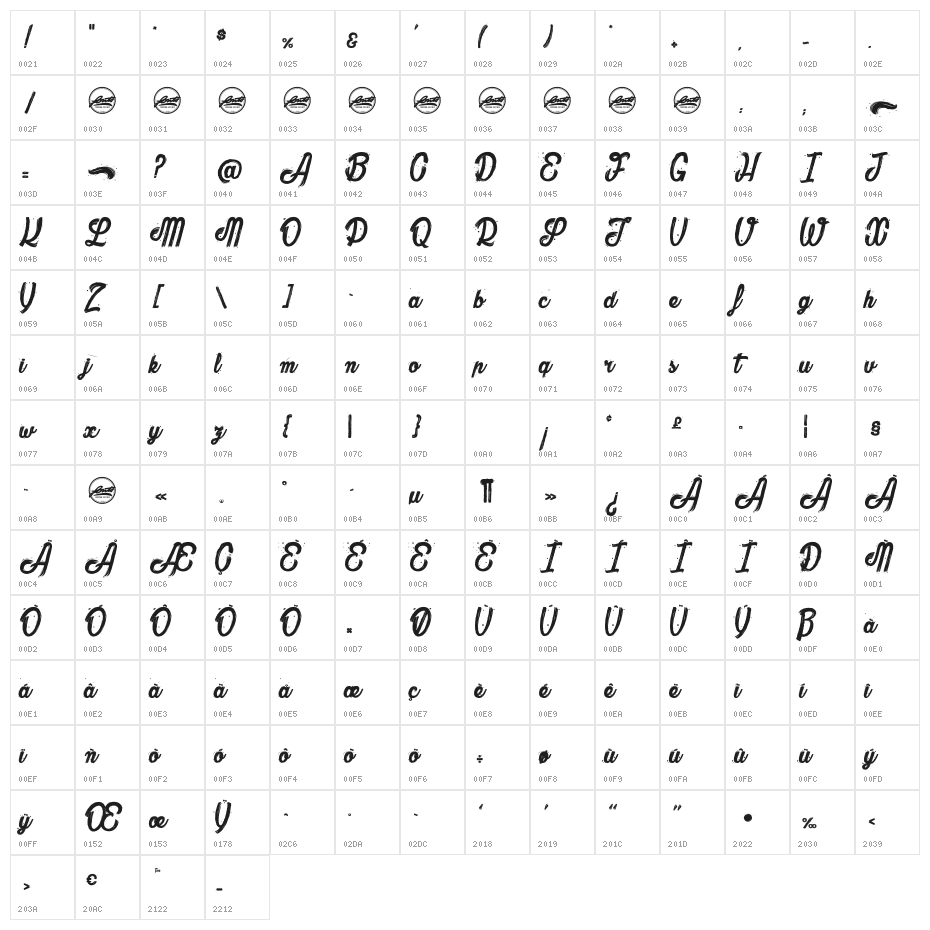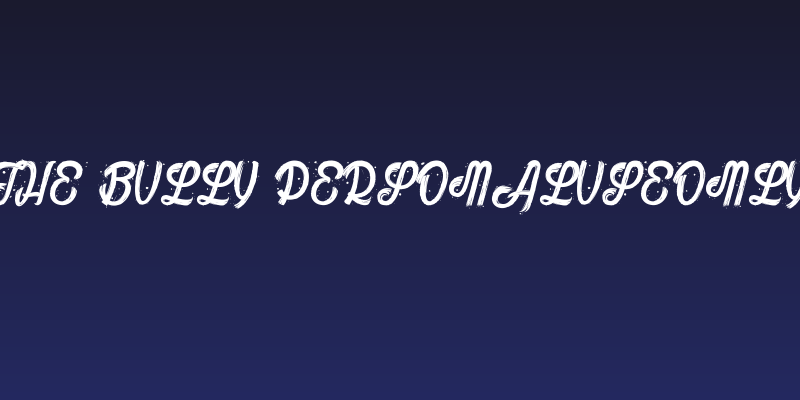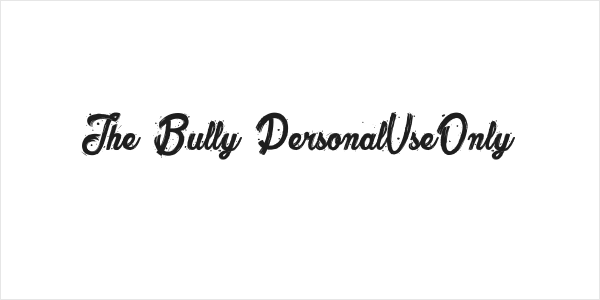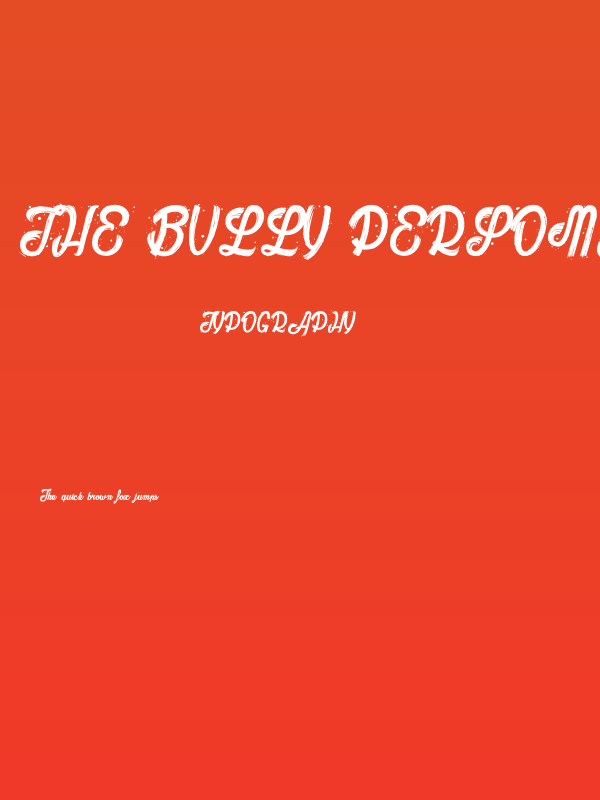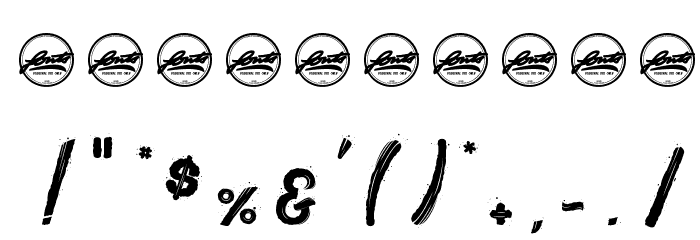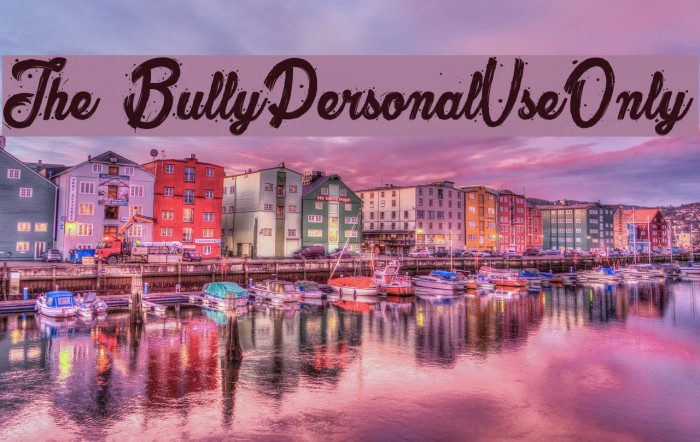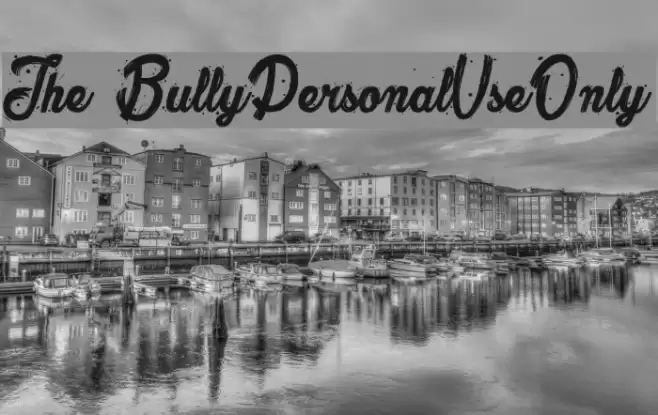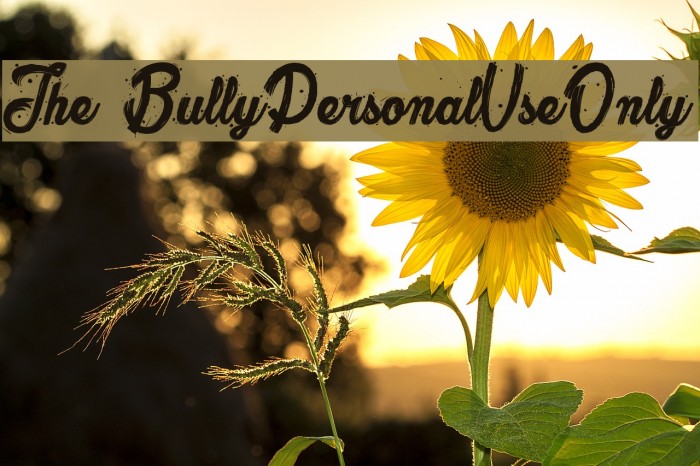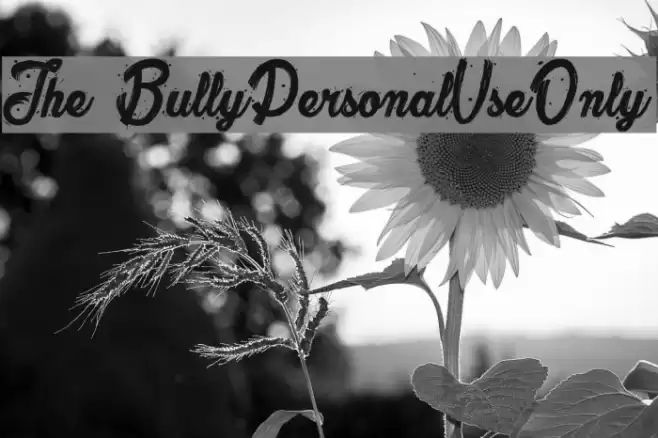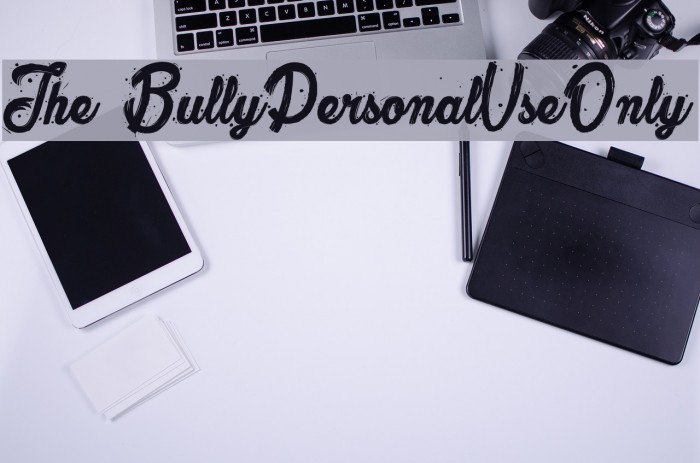
The Bully_PersonalUseOnly Font
✎ Script
| Projets proposés | Ideal for branding, posters, album covers, and any design needing a bold, artistic touch. |